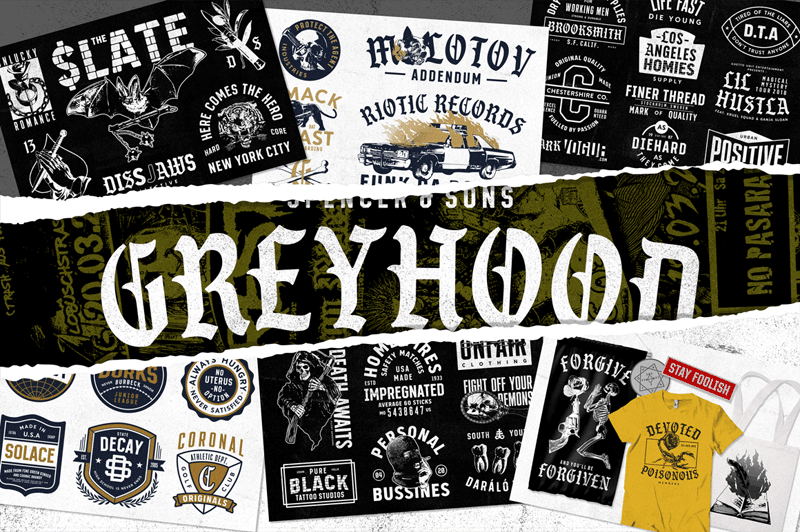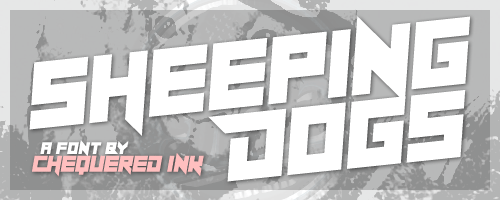
Anda sedang mendesain sertifikat, piagam penghargaan, atau ijazah? Postingan kali ini kami dedikasikan untuk Anda. Here we go, rekomendasi font untuk piagam, ijazah dan sertifikat!
Download 35+ Font Sertifikat, Ijazah, & Piagam Penghargaan – Bila boleh disingkat, sertifikat adalah bukti kepemilikan atas sesuatu. Sesuatu tersebut bisa berupa hal material maupun non-material.
Nah, penggunaan sertifikat pun amat beragam. Mulai dari bukti kepemilikan barang seperti sertifikat tanah. Bukti kepemilikan skill seperti sertifikat kursus. Hingga bukti menjuarai kompetisi seperti sertifikat penghargaan.
Pada kesempatan ini kami akan bagikan kumpulan font untuk sertifikat yang bagus. Yang tentunya dapat memudahkan Anda memilih font diantara ribuan font yang ada di internet.
Sebelumnya, ada beberapa pertanyaan terkait font sertifikat yang sering ditanyakan, seperti berikut ini.
Apakah ada Aturan Harus Menggunakan Jenis Font Tertentu?
Tidak ada. Sejujurnya, tidak ada aturan tertulis maupun tidak tertulis mengenai jenis font yang harus digunakan saat membuat sertifikat.
Anda bisa menggunakan font berjenis Serif, San-Serif, Slab, Script, Stencil, Typewriter, hingga font berjenis Retro.
Bebas. Yang jelas, Anda harus memastikan bahwa orang lain tidak kesulitan saat membaca isi konten sertifikat yang Anda buat.
Apa Saja Font yang Bagus untuk Sertifikat?
Nah, oleh karena tidak adanya aturan tersebut, kita semua dibebaskan menuangkan ide & imajinasi dalam mendesain sertifikat.
Semua jenis font bisa kita gunakan. Dan… Tentunya semuanya juga bisa saja bagus, asalkan sesuai dengan konsep desain sertifikat yang Anda bawa.
Tanpa berpanjang lebar lagi berikut ini inti dari artikel kami kali ini.
Check these out!
35+ Font untuk Sertifikat & Piagam Penghargaan Terbaik
Tak perlu bingung dan galau lagi, silakan pilih satu diantara lebih dari 30 font di bawah ini untuk mendesain sertifikat sekarang juga!
#1 – Alice in Wonderland
Font sertifikat pertama yang bisa Anda coba adalah Alice in Wonderland. Penasaran dengan desainnya? Langsung download dan implementasikan saja ke desain Anda.
#2 – Black Stoner
Selanjutnya ada Black Stoner. Creator font ini adalah KONGFONT. Big appreciate untuk mereka atas karya yang luar biasa ini.
#3 – Bombaya
Selanjutnya adalah Bombaya. Menurut kami Bombaya merupakan salah satu font piagam penghargaan terbaik yang bisa Anda gunakan secara gratis.
Jenis font serif yang memadukan style classic dan modern ini sangat pas digunakan untuk berbagai macam tema desain.
#4 – Black White
#5 – Voice In My Head
#6 – Pirata One
#7 – Black Gunslinger
#8 – BlackBox
#9 – Morgana
#10 – Black Bone
#11 – Sheeping Dogs
#12 – Abaddon
#13 – Font Piagam Penghargaan: Greyhood
#14 – Font untuk Piagam: Aesthetic
#15 – Lifecraft
#16 – Black Shadow
#17 – Avalen Rekas
#18 – Black Wine
#19 – Ghost Rider
#20 – Black Wall
#21 – Font Ijazah: Black Diamond
#22 – Final Frontier
#23 – New Gothic Textura
#24 – Shadow of Security
#25 – Potsdam
#26 – Germania
#27 – SF Ironsides
#28 – Viking Hell
#29 – Tannenberg Fett
#30 – Black Jack
#31 – Hoka Red
#32 – Ballistic
#33 – Font Piagam Penghargaan: Saltwater World
#34 – Font Ijazah: Mars News
#35 – Font untuk Sertifikat: Sharon
#36 – Font Sertifikat: Rocket Chicken
Kesimpulan
Inti dari pemilihan font dalam pembuatan ijazah, sertifikat, dan piagam penghargaan adalah tidak menyulitkan pembaca memahami isi sertifikat yang Anda buat. Baik itu nama, acara, dan segala isi dari sertifikat.